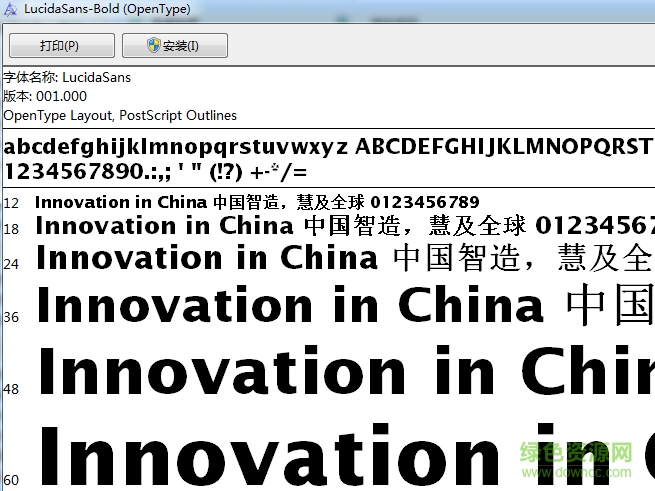
lucidasans bold字體
lucidasans字體是一款極具個性的英文字體,字體的線條較粗,相比較一般字體,該字體能夠更好的讓人記住,非常適合用于廣告設(shè)計(jì),對于從事平面設(shè)計(jì)的用戶來說,更是經(jīng)常和字體打交道,這款是必不可少的一款英文字體,趕快來免費(fèi)下載試用吧!
lucidasans字體